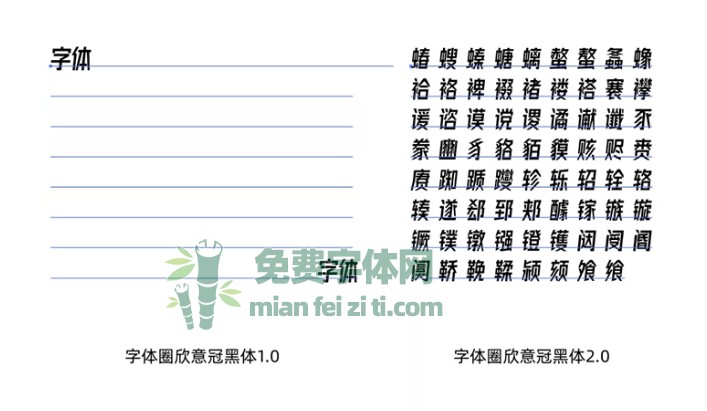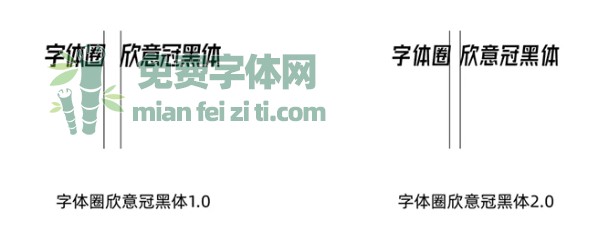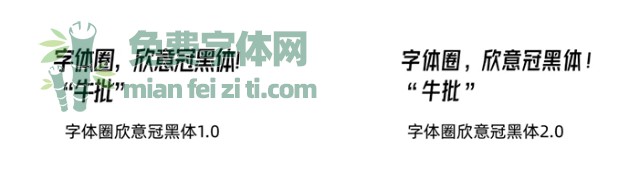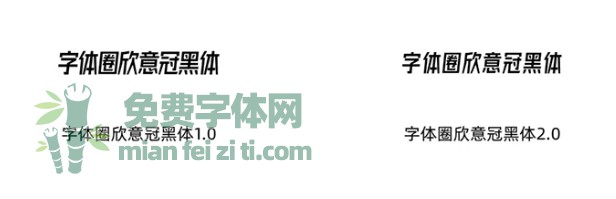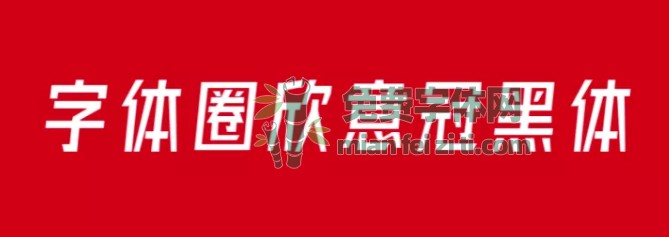
字体圈欣意冠黑体v2.0更新了什么?
1、添加了新的汉字字符
2、空格字符宽度减小
3、中文标点调整
4、所有字符调整默认间距
调整后比之前舒服一点,不会觉得很挤。 到此所有简体中文已经全部更新,应该不会有缺字,如果出现错字请联系我~
hi大家好,在上周三发布了我的这套免费商用的字体《字体圈欣意冠黑体》,正式的跟大家见面了。经过这几天最后万般努力的调试与修改,今天正式开放下载!(没料到今天周一还在放假)
发布的时候时间过于仓促,更多的应用展示及很多想说的话都来不及说。这次更完整,同样希望您能看完。
字体的版权问题,是所有设计师,最闹心的问题,系统里自带的寥寥无几的免费字体,几乎是没办法满足设计需求。基本上市场一套字的商用费用在每年5000人民币以上,侥幸心理偷偷用被字库公司发现,一封律师函,几十万赔偿也是分分钟。(侵权费比授权费还要高十倍以上)
发现很多朋友不知道做一套字体需要花多少工夫,也不知道字体是干什么用的。这么说吧,一套最基本的字体,也需要涵盖6763个汉字,超级字库更是将近30000字符。每一个汉字都不一样,而这每一个汉字都是由一笔一划拼接组成,手写字需要一笔一划的去写,艺术字也是如此。
那字体是干什么的呢,一般来说字体是对设计行业的朋友作用占比较大,因为在商业场景下电商、LOGO设计、门头招牌、海报、包装、包括很多的电视电影节目等等很多能看到文字的地方,都需要字体。但因为传统的黑体,楷体,宋体,隶书等不能完全满足现在的需求,毕竟现在是个高审美高要求的时代!
那非设计行业的有没有用呢?明确的告诉你,也有用。比如你是做自媒体的,视频中需要字幕,公众号配图需要字体,官网需要字体,连最基本的做简历做PPT也需要用到字体。
我在2018年已经有做套字体的想法,当时初步的做了上百个字形。当时说希望能尽快跟大家见面,虽然现在这套字已经不是当时那套字。
2019年,我创办了字库品牌(左字zofont),因为产能太低还没开张,一年最多就开发一两套字体,还不一定有人喜欢,但其实我挺喜欢做字的,这一年我也做了好几套字体。
有人问定制一套字体要多少钱,大部分报价都在10W以上,大企业定制品牌字体成本更是往百万走,尽管我们日常所需只需要用到几个字或几十个字,但不可否认一套字体的价值。
这是一套倾斜类字体,同类免费字体还有前几月优设网发布的《优设标题黑》,这套字很优秀,短短几个月到处都能看到它的身影。(注:《优设标题黑》不是我设计开发的,只是顺带提一下这套字我个人很喜欢,不要再问了哈)
这套字叫《字体圈欣意冠黑体》,欣意=心意。对于这套字体的发布,不希望只限于这是一套字体,我更想纪念一件事情,那就是今年的疫情。我想以我的专业技能为抗疫发声,希望疫情能早点退去,早点让祖国,让世界恢复往日的繁华。
这套字涵盖国家GB2312标准的6763个中文字符,52个英文字符,10个阿拉伯数字,若干个中英文符号,按需添加若干个生僻字,共7000余字符。因为字形偏高瘦型,测试过这套字倾斜8°有点奇怪,最后选择倾斜6°,视觉平衡多了。
这套字从开始设计到修改到最后开发,用了将近一年的时间(字形设计制作6个多月,后期修改+开发3个多月)。这大半年里,我没睡几个安稳觉,凌晨三四点睡觉是常态,有时通宵然后去洗个澡继续,有一段时间感觉有点透支,不过很庆幸还是坚持下来了,现在想想以后大家的字体列表有我的字就有点开心。
花了这么多精力去做这件事情,也不知道我做的这件事对不对,不知道发布之后有多少人看,多少人留言,多少人赞赏,多少人转发,多少人使用,受多少人喜欢(因为综合阅读量都在100以内,所以很害怕刚发布就凉了,预热的文章阅读量到现在也就600多)。每次出去看到海报上别人的字体,我就经常幻想着以后这里换上我的字体会是什么样